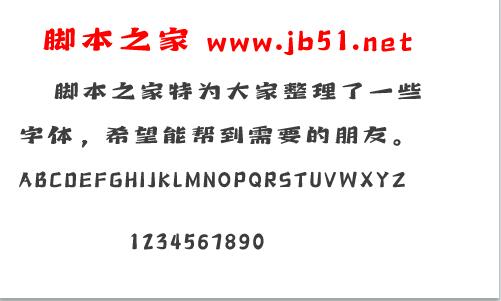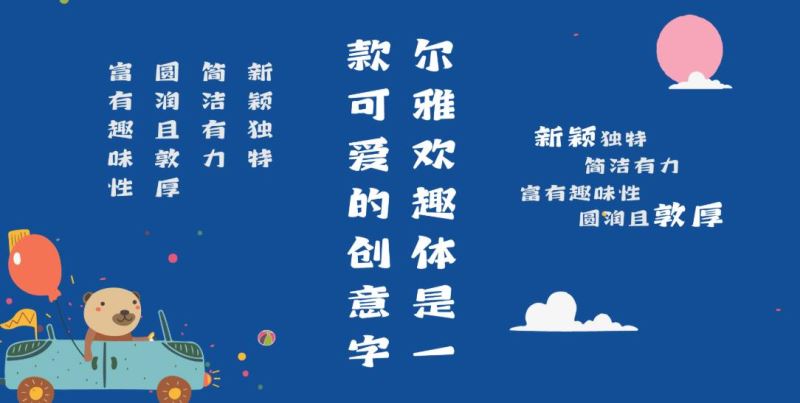
爾雅歡趣體是一款可愛的創(chuàng)意字,這款字體筆畫豐肥圓潤,飽滿有生命力,粗細(xì)富有變化,橫筆畫長、豎筆畫短,整體結(jié)構(gòu)顯得略微寬扁,字中大量的采用曲線和直線的組合設(shè)計,整套字看上去新穎獨特,簡潔有力,圓潤且敦厚,富有趣味性。
爾雅歡趣體柔和有趣,隨性而又不拘謹(jǐn),妙趣橫生,字體具有很強(qiáng)的親和力,靈動的筆畫給人一種親和可愛之感。
字體的部分撇筆畫、捺筆畫、點筆畫、帶有裝飾小鉤并且小鉤的位置都在線條最粗的一端,非常的可愛有趣。